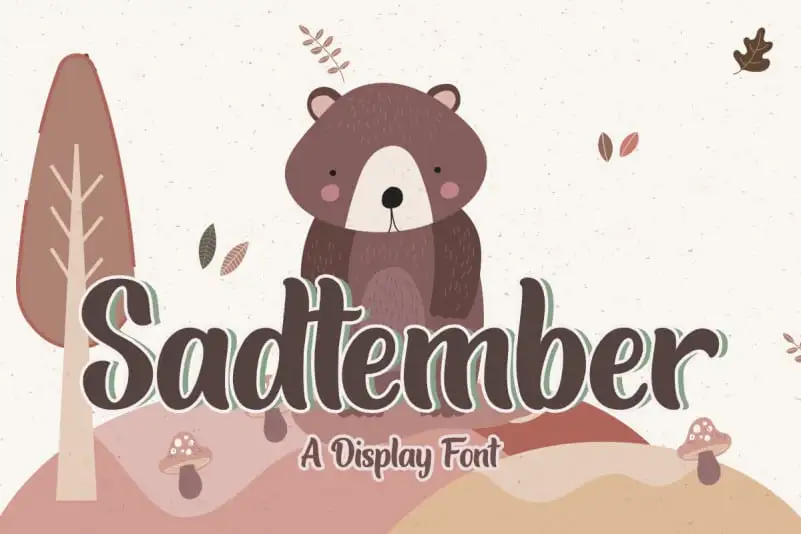
A Sadtember Display Font é uma tipografia de destaque, criada para quem busca expressar estilo e originalidade. Com seu estilo levemente adoçado, essa fonte se adapta perfeitamente a criações visuais como logotipos, embalagens, símbolos de marca, camisetas customizadas e projetos de branding. Seja para adicionar uma pitada de leveza ou um toque mais forte, esta fonte surge como uma excelente escolha para qualquer projeto criativo que precisa destacar-se. Como uma versão display da família Sadtember, ela traz precisão e impacto em cada letra, garantindo que seu design seja notado na cena do design visual. Ideal para designers que buscam diversidade no estilo de seus projetos, a Sadtember Display é um recurso indispensável para qualquer coleção gráfica.